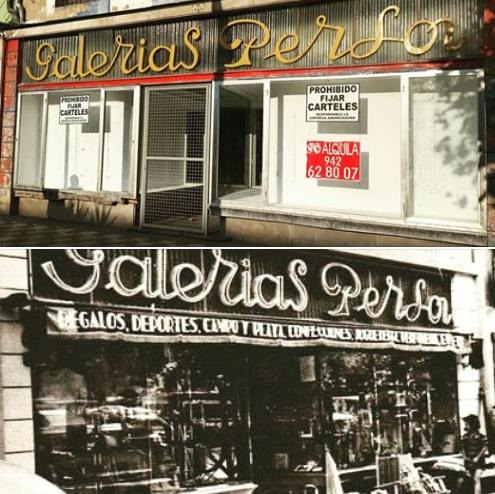
Desde Santatipo se pretende salvar y rescatar los rótulos, para que sean preservados y puestos en valor como un Patrimonio Gráfico de las ciudades. Como desde aquí se ha dicho muchas veces, esas letras trascienden a la memoria local. Ya se ha comenzado a rescatar algunos rótulos, y poco a poco esta iniciativa va calando en las calles.
Se han sumado otros dos, por sendos avisos, a esta colección. Uno es el de la Joyería Fuensat en la calle Guevara. Parte del luminoso se cayó, con esa tipografía medieval y escudo de armas. Es lo que se ha podido rescatar, pero lo importante es que el rótulo principal, con ese juego tipográfico de la «F» está en riesgo y por tanto en seguimiento.
Con esto, poco a poco se va ampliando el material gráfico que desde Santatipo se está rescatando, con la idea de poder ponerlo en valor en un espacio o exposición. Aún queda mucho trabajo por delante y hay varios rótulos que están riesgo en toda la región, como por ejmplo el de las Galerías Persas de Laredo.